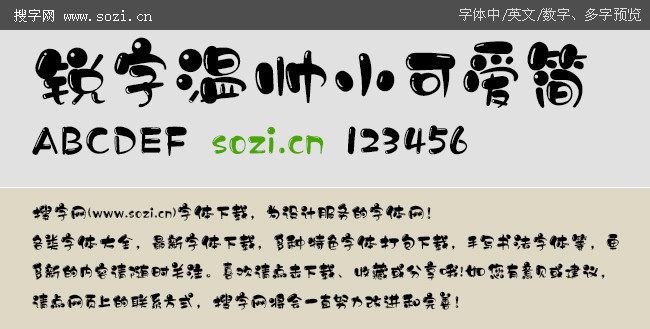
銳字溫帥小可愛簡(jiǎn)
搜字網(wǎng)提供一款銳字溫帥小可愛簡(jiǎn)中文字體下載,銳字溫帥小可愛簡(jiǎn)在可愛體的基礎(chǔ)上添加了高光,更加有立體感。字形溫潤(rùn)飽滿、親切乖巧,筆畫不拘一格、粗細(xì)對(duì)比協(xié)調(diào)、簡(jiǎn)化變形有新意且不失識(shí)別性,營(yíng)造了一種輕松歡快、充滿趣味性的氛圍;非常適合兒童海報(bào),包裝設(shè)計(jì),網(wǎng)頁(yè)設(shè)計(jì)等設(shè)計(jì)使用!颈咀煮w供個(gè)人非商業(yè)免費(fèi)使用,如需商用請(qǐng)聯(lián)系作者授權(quán)】